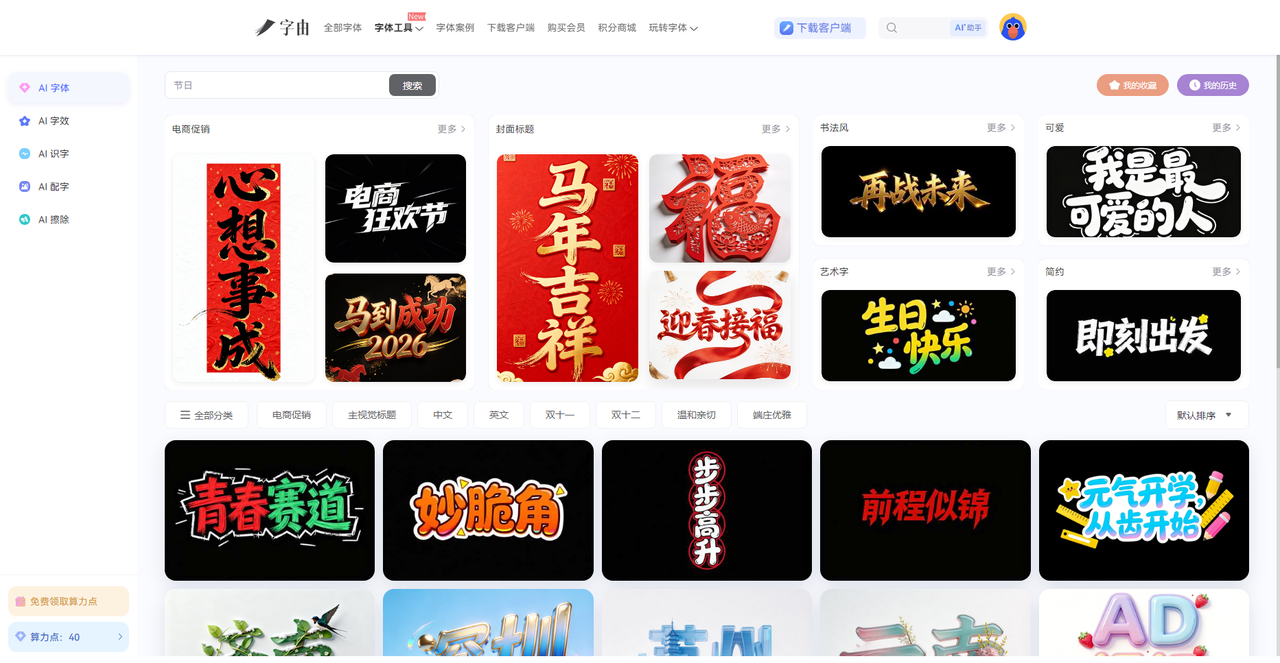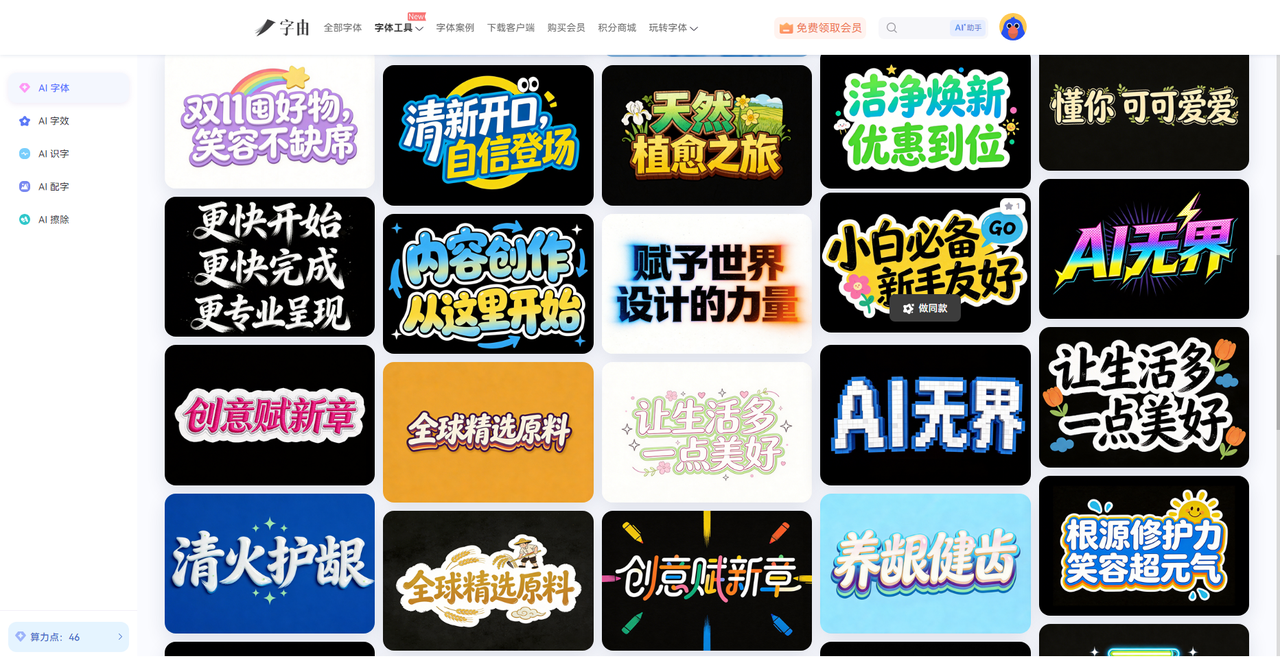
这几个艺术字生成器不用下载,打开网页就能用
以前如果要做艺术字的话肯定要自己设计再加上一些特殊效果处理,这一套流程下来,少说也要一个小时,如果你还想再做细致一点,不花时间肯定是做不下来的。但是现在有不少艺术字生成工具,打开网页,输入文字,选个风格,点一下,几十秒就能拿到一张带特效的艺术字。不用下载任何软件,不用安装任何字体,打开浏览器就能用。今天我就推荐5 个亲测好用的艺术字生成工具,让你不再为艺术字发愁。
字由不仅仅是字体库,还是一个AI工具箱,其中就包括支持艺术字生成。你不需要安装任何软件,打开浏览器,进入字由官网,找到【AI字体】功能,就能开始设计。整个过程完全在线,输入文字,选择模板,实时预览效果,最后下载透明背景PNG。接下来我会教大家如何使用字由在线生成艺术字:
第二步:在搜索框里输入你想要的效果,比如“霓虹”“金属”“手写”“国潮”“3D”,系统会筛出对应的模板。搜索结果会展示各种风格的预览图,比如:
- “午夜电台”:复古霓虹风格,适合音乐海报
- “碎纸机”:破损撕裂效果,适合摇滚、街头文化
- “Surmmer”:夏日活泼风格,适合派对、度假主题
- “元宵节快乐”:喜庆节日风格,适合促销活动
每个模板都有预览图,鼠标滑过就能看到用你的文字实时展示的效果。
第三步:选一个顺眼的模板,点击“做同款”,把模板里的文字换成你的标题(最好和模板字数一样)。点击“立即生成”,等20-30秒,就能拿到一张高清艺术字图片。模板分类很细,从节日、电商到国潮、科技,基本覆盖了日常设计可能用到的所有风格,你总能找到一款对胃口的。
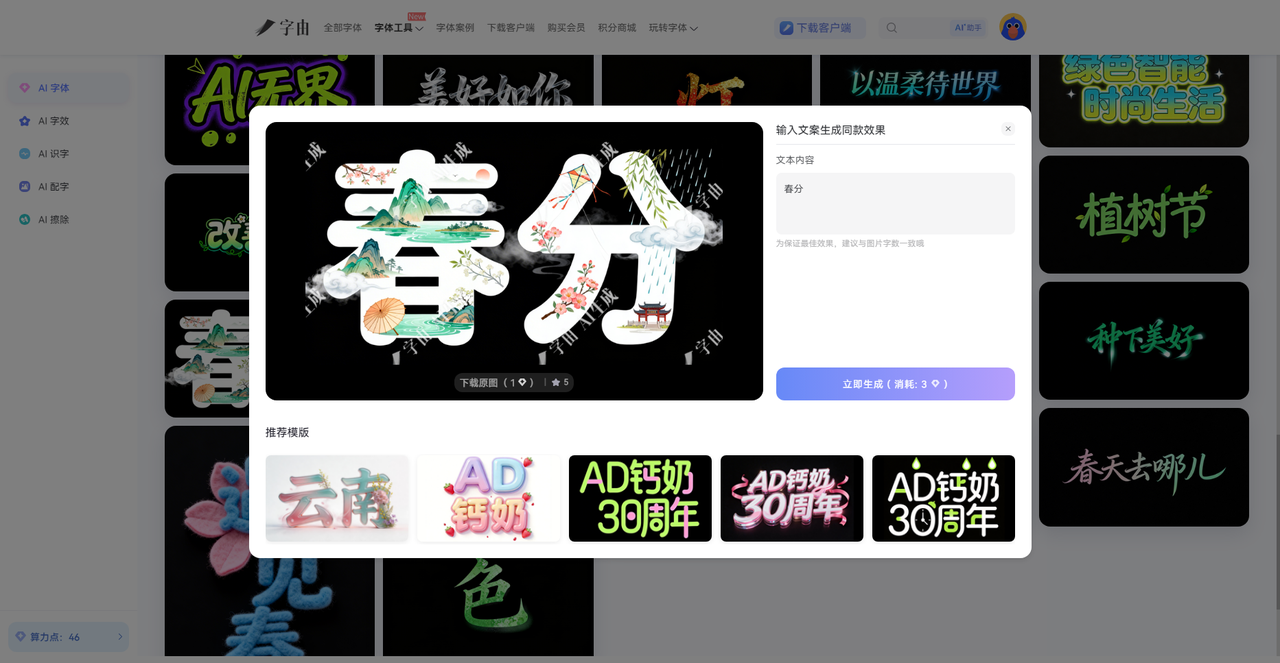
当然,就算你没能在这里找到合心如意的模板,也可以去AI 字效逛一逛,比如发光、金属、水彩,可以用字由的【AI字效】。内置400多种特效模板,点一下就能加,不用自己调图层样式。同样是透明背景PNG,拖进设计软件里直接用。
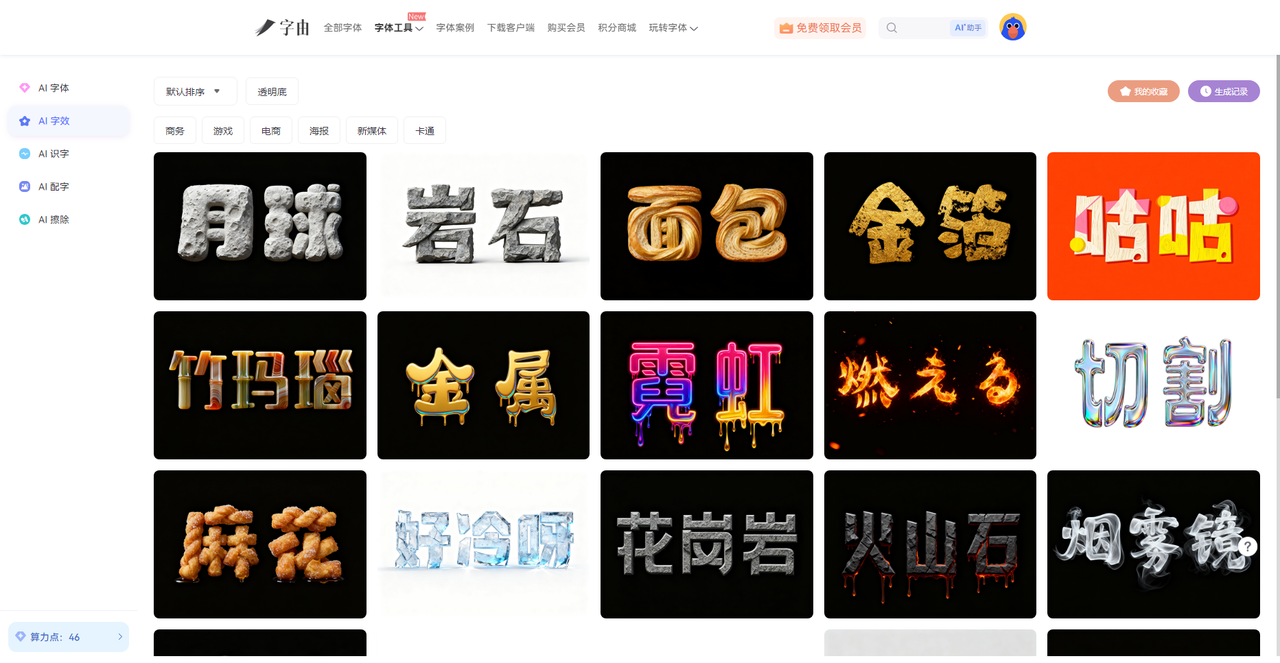
2、 Fonts Generator
Fonts Generator 是一个专注于文本艺术字的在线工具。它的操作也非常简单:在输入框里输入你的文字,然后从下方选择字体样式。分类包括:Recent、All、Cool、Fancy、Cursive、Small、Bold、Glitch、Latter Case、Symbol-Text等。选中后,文字会实时转换成对应的艺术字效果。从截图看,它提供了“Text Art”和“SquaredLetters”“Retovibes”等风格,适合喜欢复古和装饰风格的用户。生成后可以直接复制或下载,完全免费,无需注册。
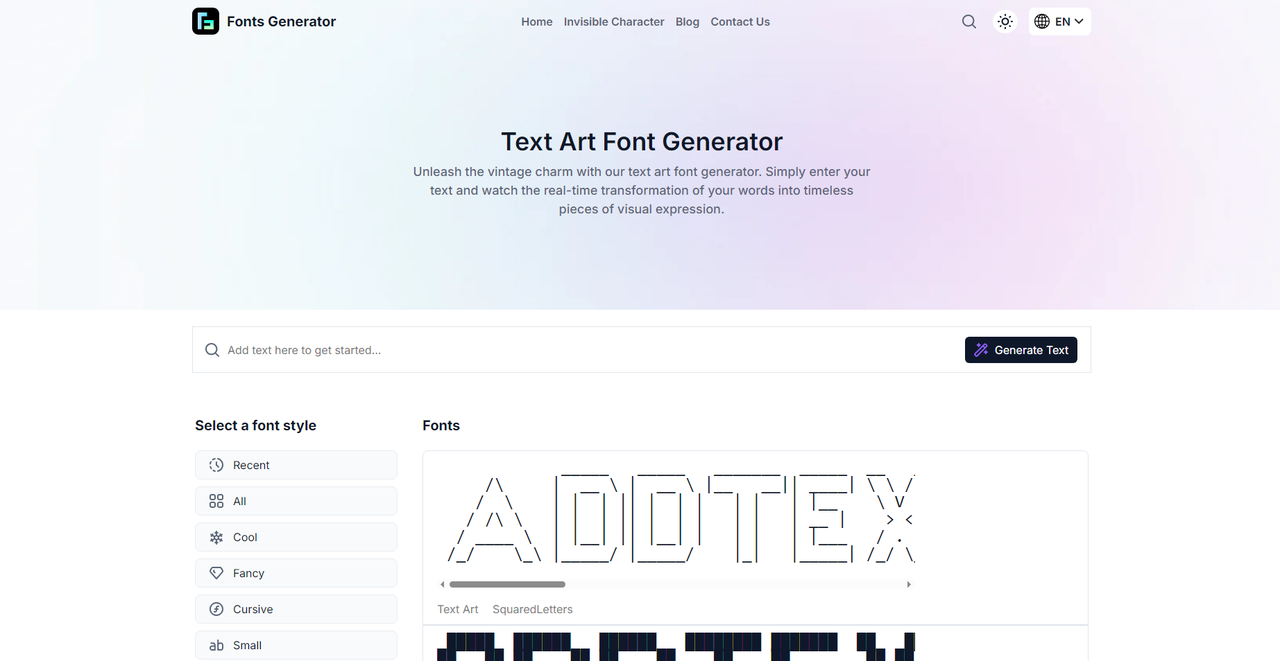
3、TextStudio
TextStudio 是一个功能非常全面的艺术字生成平台。它的界面左侧有丰富的参数调节选项,中间是实时预览,右侧可以下载。它的核心功能有:
- 样式预设:提供多种特效模板,比如“WORD ART”等
- 参数调节:可以调整缩放、字符间距、行高、文字曲线、旋转角度
- 动画效果:支持生成动态文字(GIF或视频)
TextStudio 的优势是调节选项多,适合对艺术字效果有精细要求的用户。比如你想要文字稍微弯曲一点,或者想调整每个字之间的间距,在这里都能轻松实现。生成的文字可以直接用在Logo、海报、社交媒体封面上。
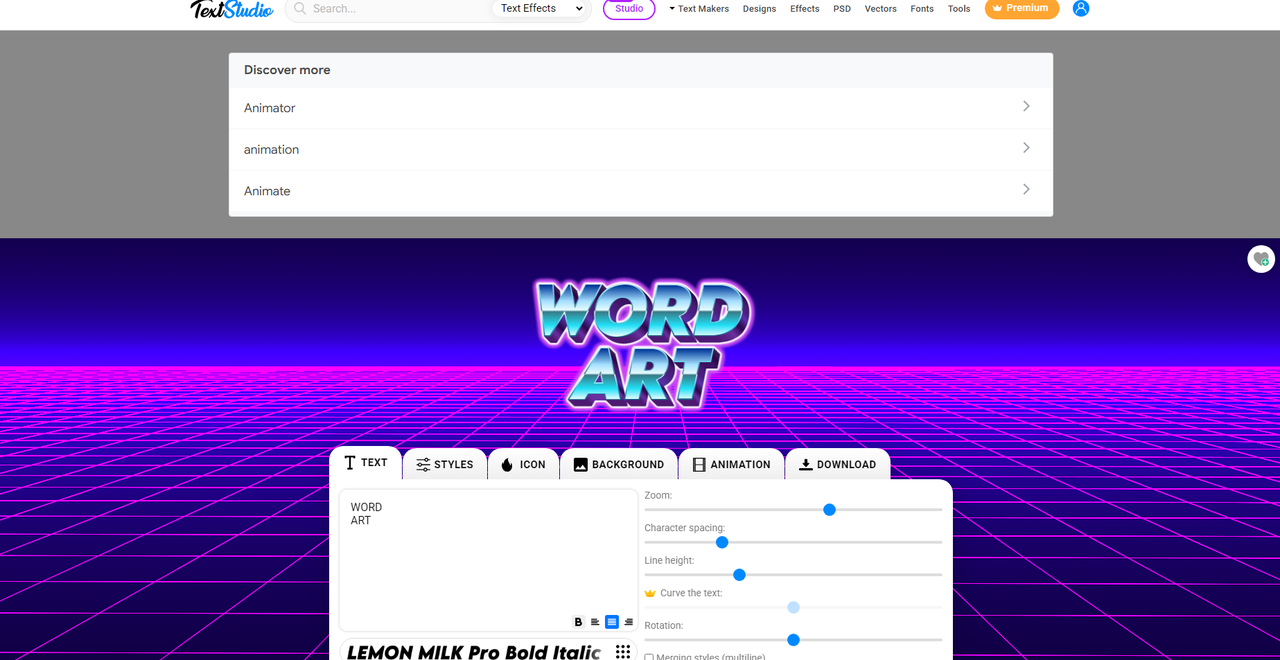
4、Cool Text
Cool Text 是一个运营了二十多年的老牌艺术字生成器,很多设计师第一次做艺术字就是从它开始的。它的风格分类非常丰富,截图里展示了各种样式:Burning、Sugar、CHICK FLICK、Orgnon、LEGAL SKATE、MIAMI、RAGE、SWORO、Happy New Year、BAD ACID、Cupid、COFFEE CUP……足足几十种。操作非常简单:选一个风格,填上文字,调整参数(如字体、大小、颜色),点生成,就能拿到一张艺术字图片。虽然界面有点复古,但胜在经典稳定,效果也够用。如果你需要快速生成各种风格的艺术字,这里是个好选择。
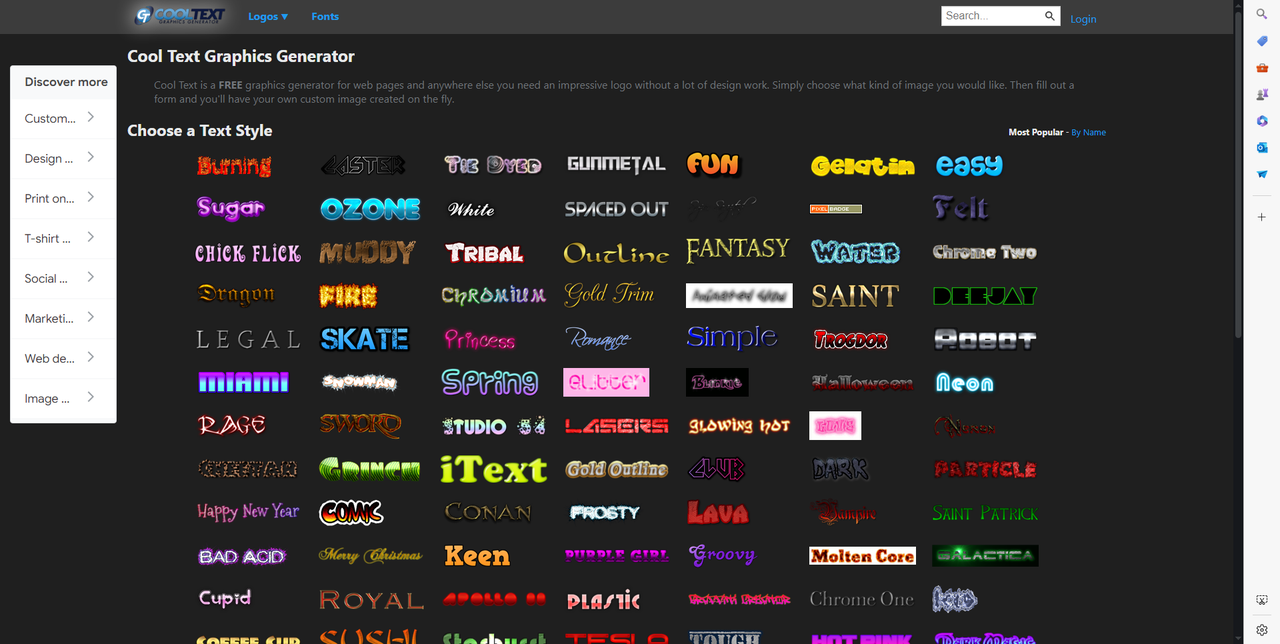
如果说工具是解决问题的,那这四个网站解决的是“想要艺术字又不知道从哪下手”的问题。Fonts Generator 让你在复古和装饰风格里找到灵感,TextStudio 给足你精细调节的空间,Cool Text 用二十多年的经验把各种风格都备齐了。而字由对我来说,是那个最快上手的——打开网页,搜个模板,填上文字,几十秒就能拿到一张能用的艺术字。它解决的不是“能不能做”,而是“能不能快”。如果你也经常因为标题字卡住,不妨去试试字由,看能不能让设计变得更加便捷。